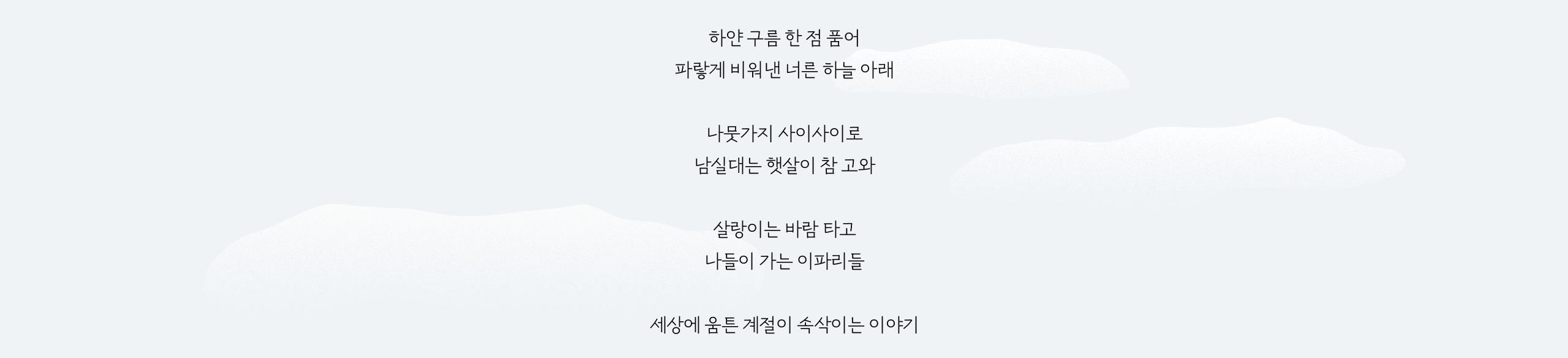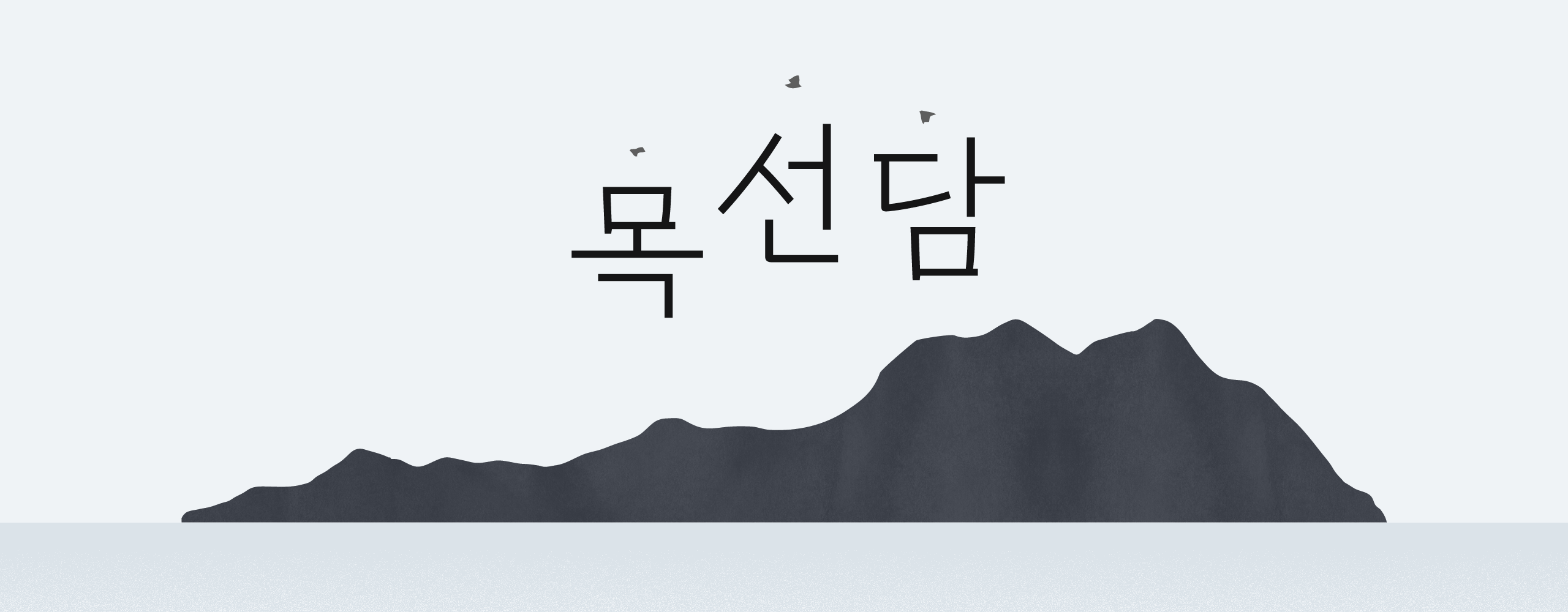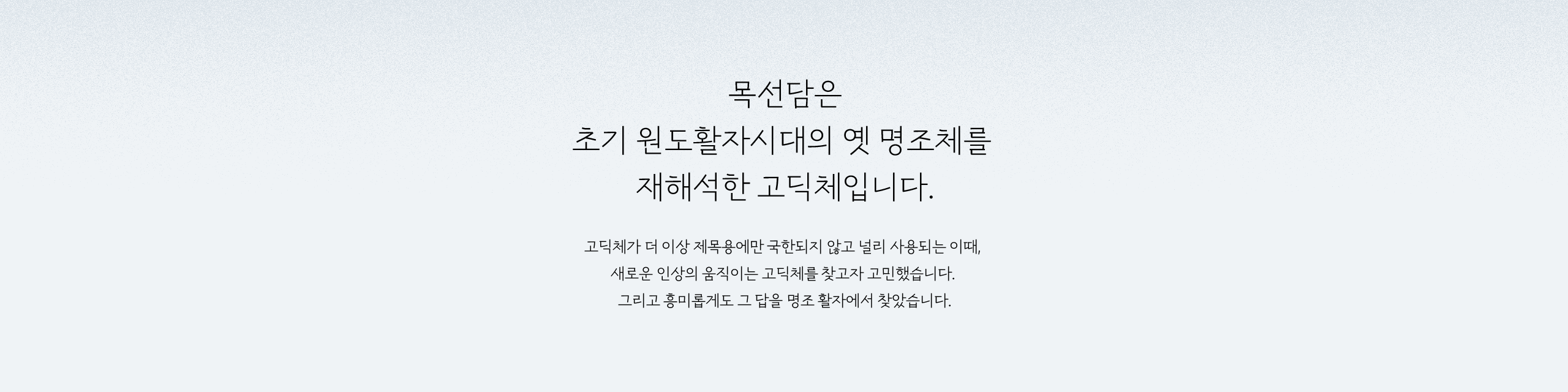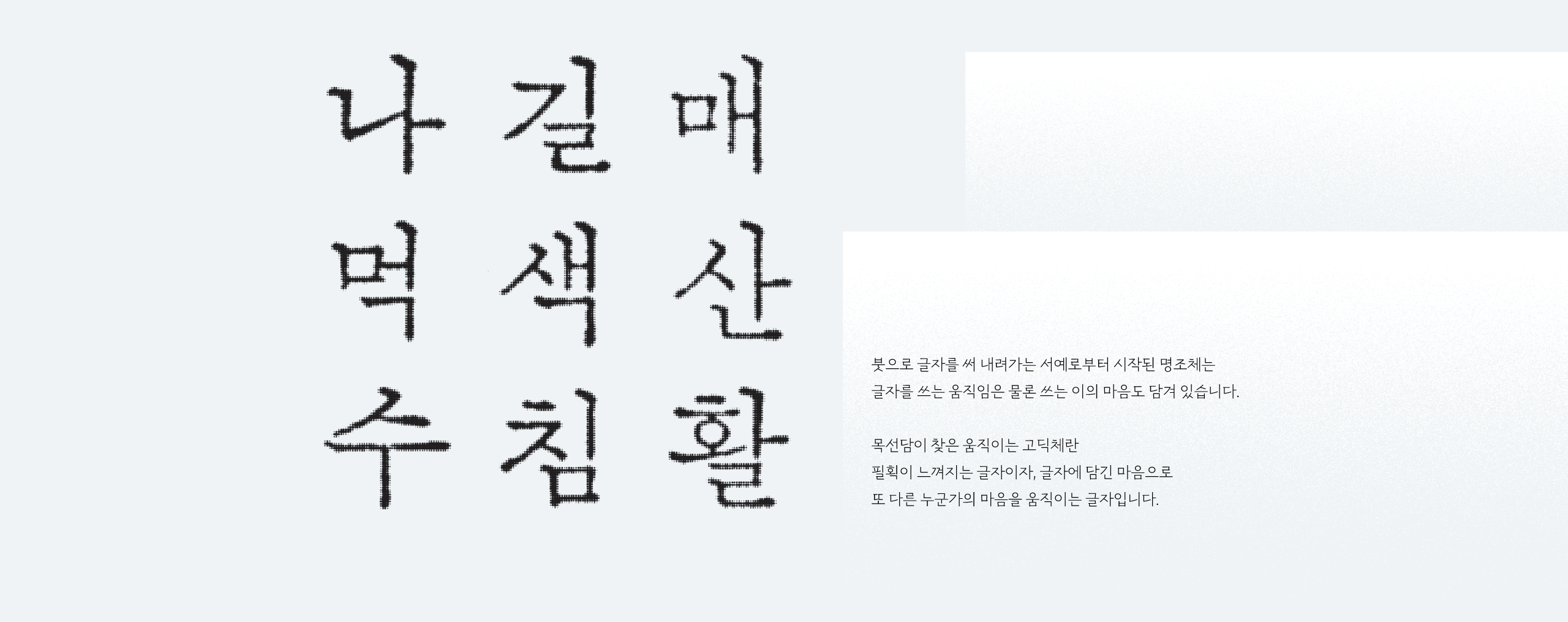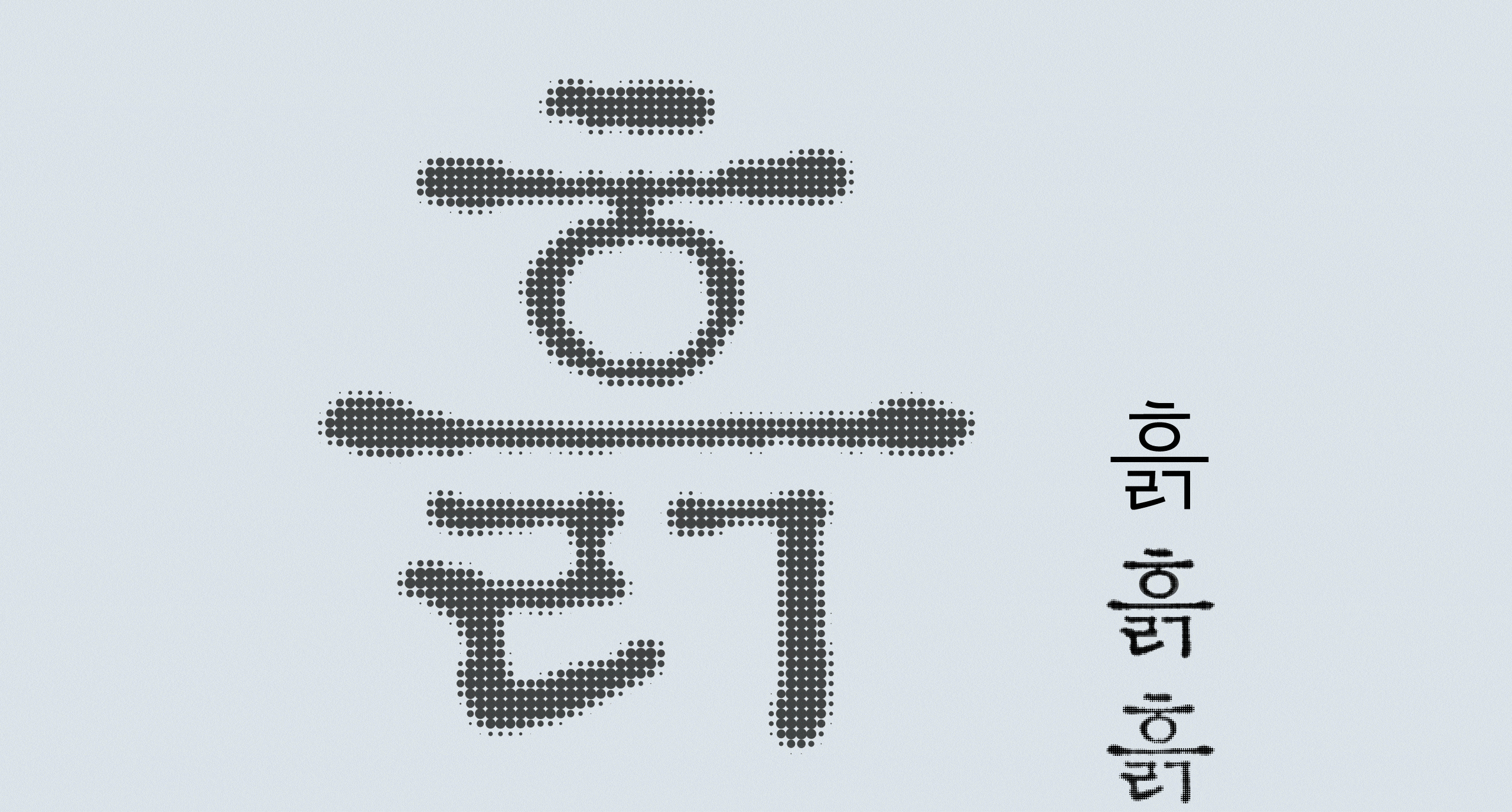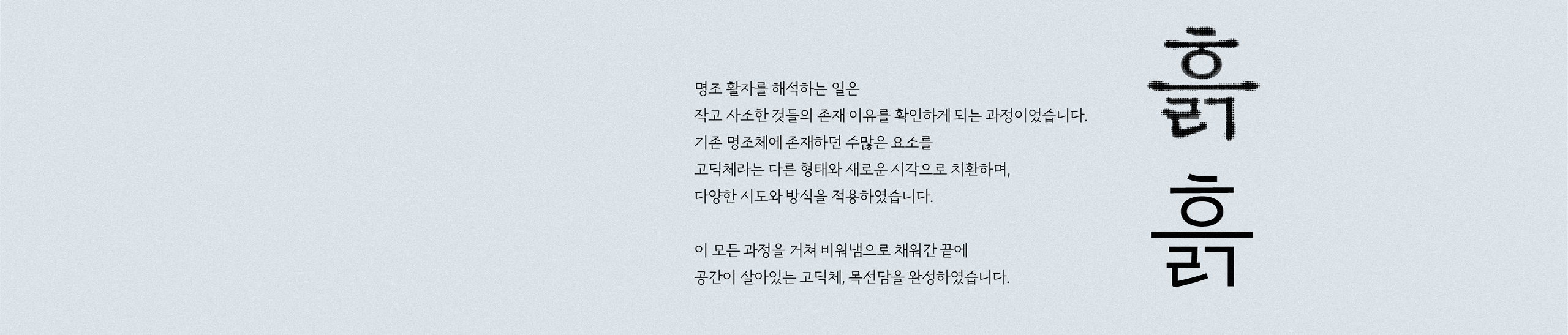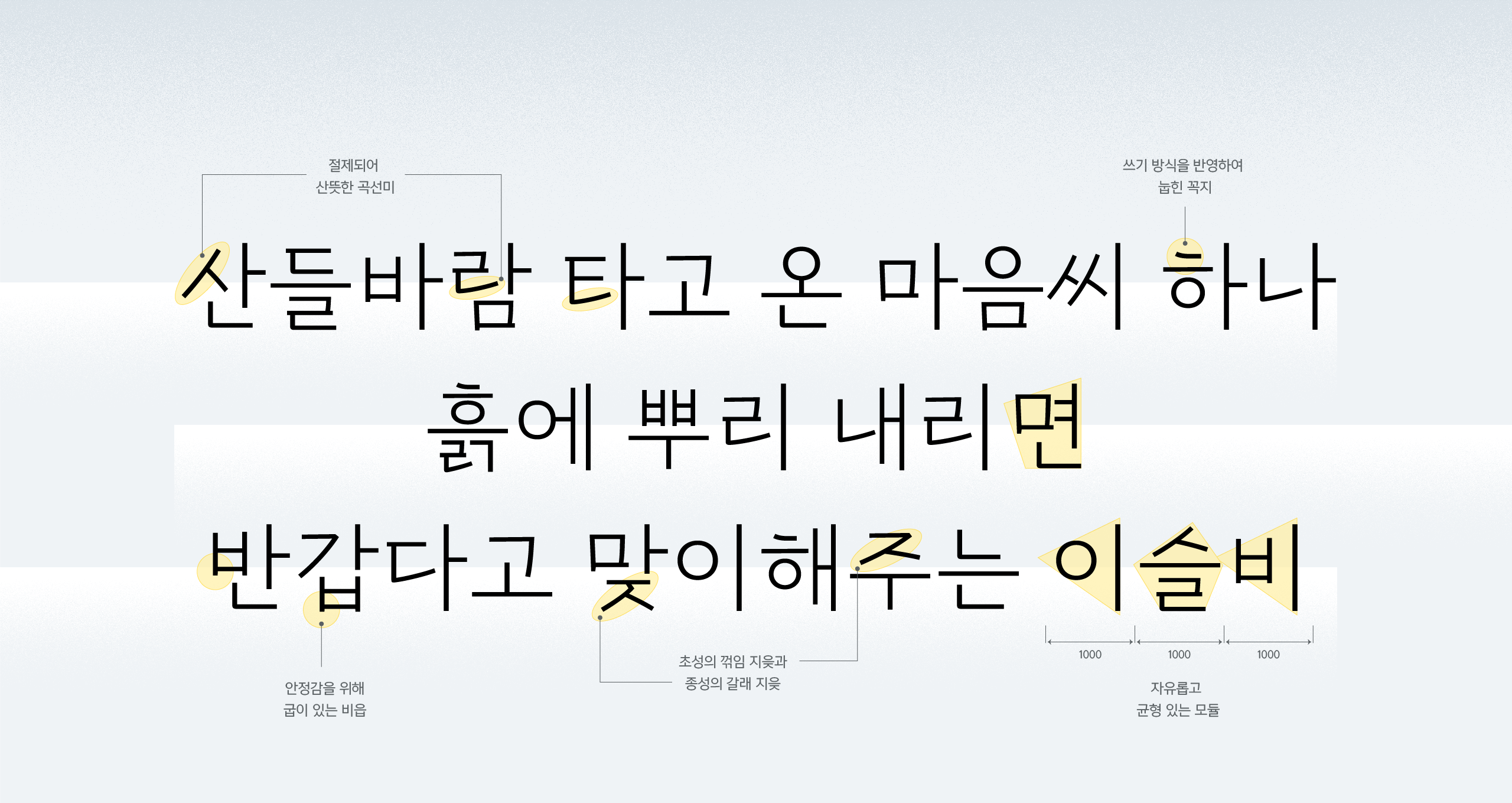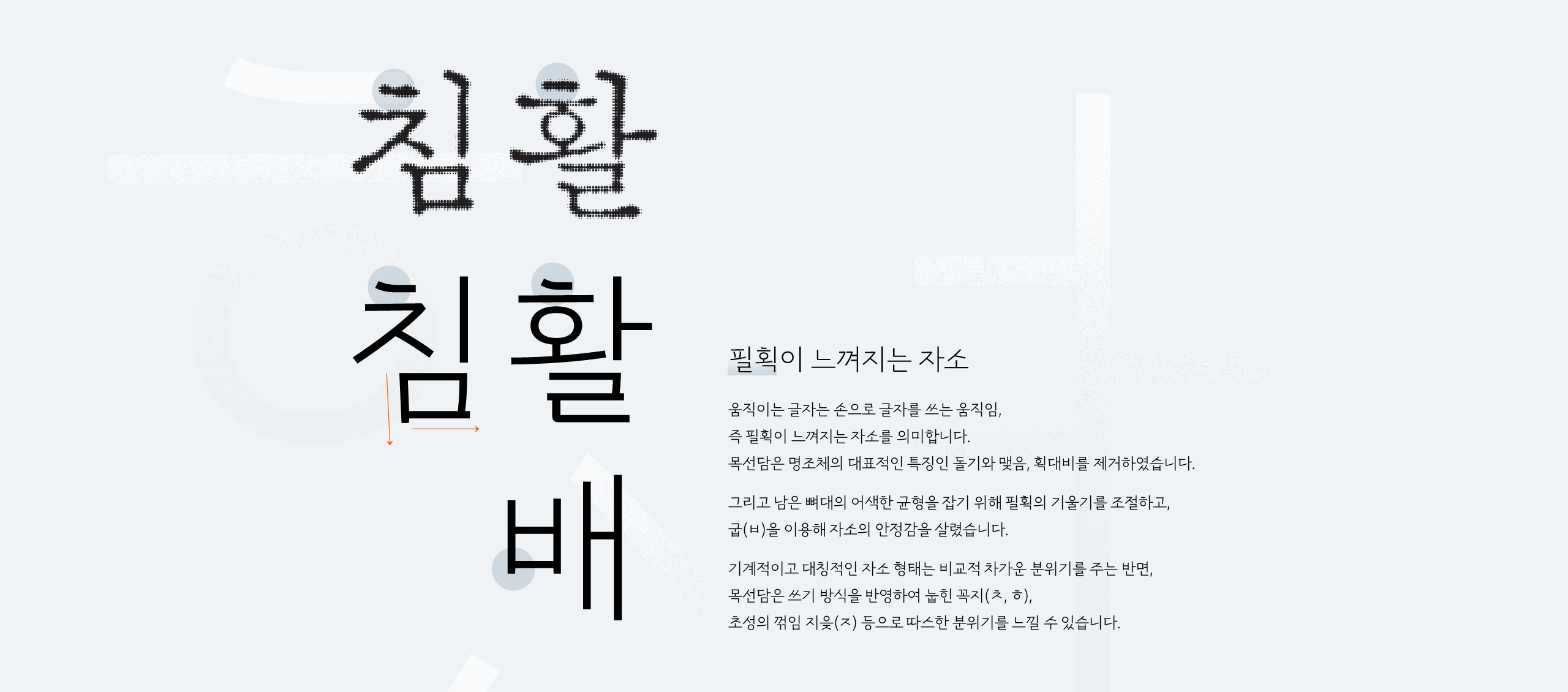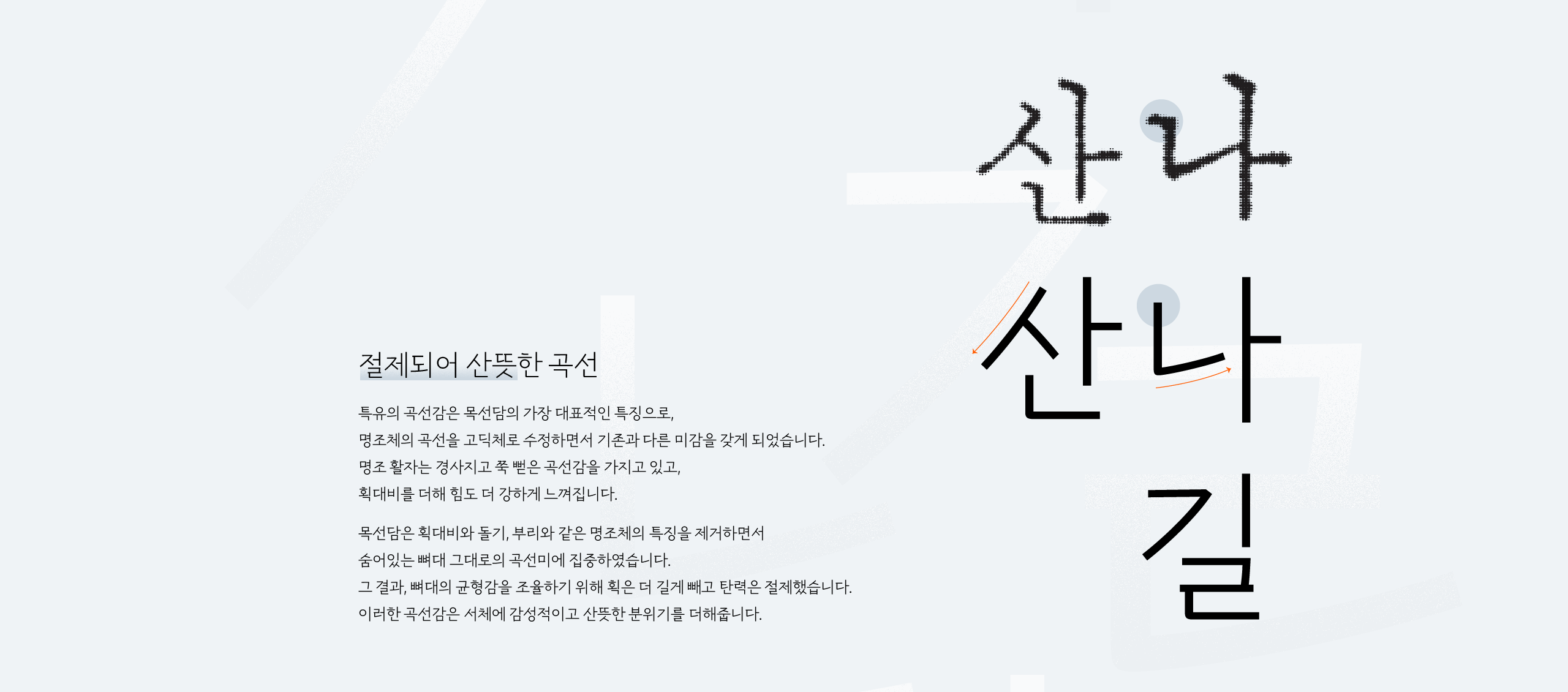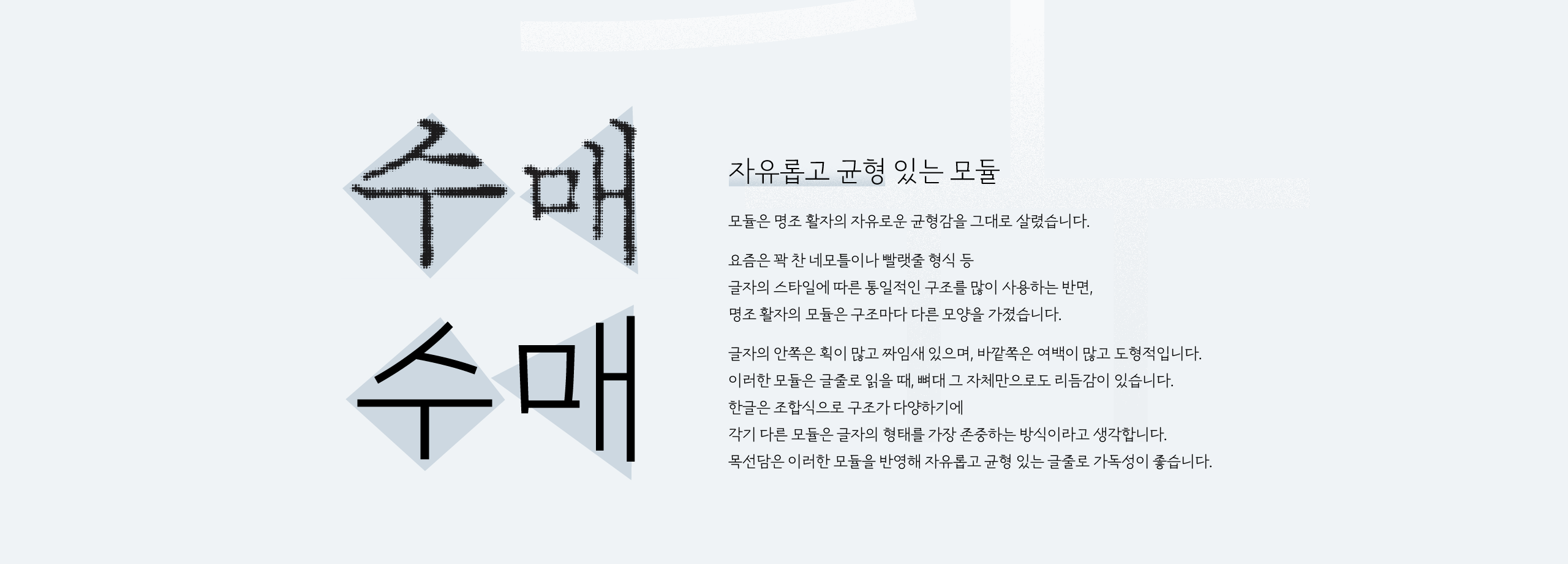
새로운 인상의 움직이는 고딕을 찾고자 고민하던 중, 흥미롭게도 그 답을 명조 활자에서 찾았다. 붓으로 글자를 써 내려가는 서예로부터 시작된 명조체는 글자를 쓰는 움직임은 물론 쓰는 이의 마음도 담겨 있다. 목선담은 초기 원도활자시대의 옛 명조를 뼈대로 삼아 고딕으로 재해석한 서체이다. 기존 명조에 존재하던 수많은 요소를 고딕이라는 다른 형태와 새로운 시각으로 치환하며, 다양한 시도와 방식을 적용하였다. 이로써 필획이 느껴지는 자소, 절제되어 산뜻한 곡선, 자유롭고 균형 있는 모듈로 공간이 살아있는 고딕체, 목선담을 완성하였다.
Yoon 목선담